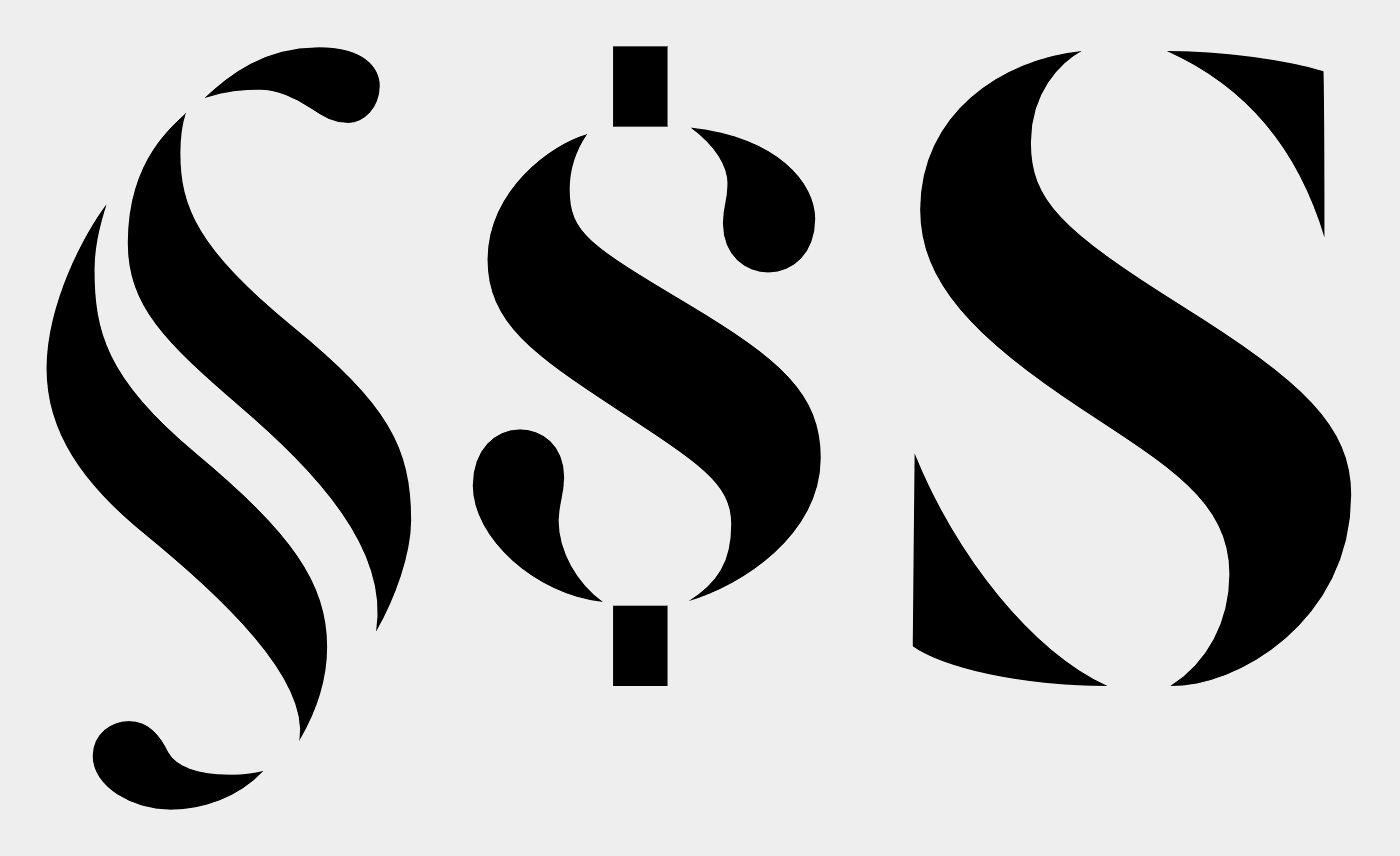
Suche Font(namen) aus meinem Logo.
Nun zu meinem Anliegen
Ich habe mein Logo erstellt mit einer Font dessen Name ich nicht mehr weiß.
Hier ein Bild
Ich habe mal so weit den Rest skizziert, wie ich meine die Font in Erinnerung zu haben:
Es handelt sich dabei Entweder um ein "S" oder um ein "§" doch ich bin mir sicher das es ein "§" war.
Leider habe ich auch keine weiteren Dateien mehr außer ein JPEG.
Ich hoffe mir kann hier geholfen werden die Font zu finden, bin aber voller Zuversicht.
ich nehme an, du brauchst eine vektor-version deines logos. wenn du die original-daten nicht mehr hast, baust du das ding in 5 minuten in einem vektor-programm deiner wahl nach. ist 30 mal schneller als den font zu suchen.
Ich hab das mal probiert, hat genau 2min 42sek gedauert:
Muss dazu alleredings beichten, dass Corel schon lief.
Schau Dir mal klassizistische Antiquas (Didot, Walbaum, Bodoni etc.) an, die Formensprache Deines Logos könnte auf eine solche Schriftart hindeuten.
Als Laie? Dafür habe ich auch echt leider keine Zeit. Suche eben die Font
Dafür sollte man sich schon etwas Zeit nehmen, um sich grundlegende Zeichenfunktionen anzueignen, mit denen sich beispielsweise solch ein Logo sehr schnell frei zeichnen lässt, ohgne das man dazu erst lange nach einem Font oder anderem vorgegebenen Rohmaterial suchen muss. Anleitungen für den Einstig in das Zeichnen mit einer Vektorgrafik gibt es beispielsweise auf YouTube zu Hauf.
Letztlich spart man sich durch ein wenig Wissen, wie man eine einfache Grafik selbst zeichnet wesentlich mehr Zeit, als man für diew Übung aufgewendet hat.
1) Geh auf www.Myfonts.de
2) Im Suchfeld »Didone« eingeben
3) Bei den dann angezeigten Schriften im Musterbuchstabenfeld »§S« eingeben
4) auf die Narziss von Hubert Jocham stoßen und anklicken
5) rechts »view all XXX fonts« anklicken
6) die dann angezeigte Liste durchsuchen und zum Beispiel auf diese hier stoßen:
Dauer der Suche: 2 Minuten  :-D
Und da gibt es noch eine Reihe weiterer Schriften, die Du sichten könntest, wenn Dir dieses Ergebnis nicht dicht genug dran ist.
Leider ist die Schriftart nicht dabei. Ich möchte noch mal darauf hinweisen das es die gesuchte Schriftart sein muss.
Mit dem nachzeichnen by e-learing ist kein Problem im Sinne der Fähigkeit.
Hier meine Nachzeichnung.
Stimmt mich zwar noch nicht zufrieden, aber ich bin zuversichtlich.
*Zusatz: Es handelt sich auch um eine Kostenlose Schriftart.
Ein Tipp fürs nächste Mal: Das wäre ein sehr hilfreicher Eingangshinweis für die Suche gewesen, weil er von vornherein zehntausende kostenpflichtige Schriften ausschließt, die man dann bei der Suche gar nicht hätte berücksichtigen müssen.
Leider ist die Schriftart nicht dabei. Ich möchte noch mal darauf hinweisen das es die gesuchte Schriftart sein muss.
Meine Darlegung des Suchweges diente auch mehr dazu, Dir zu zeigen, wie man bei der Suche vorgehen könnte. Um weiterzukommen, würde man nach dieser ersten Suche alle ähnlichen Schriften auswählen und bei jeder einzelnen noch einmal gesondert all jene Schriften unter die Lupe nehmen, die für die Ausgangsschrift als ähnlich empfohlen werden. Das kann eine zeitraubende Angelegenheit sein – und deswegen hat der geschätzte Kollege Catfonts nicht Unrecht, wenn er schreibt, dass der Aufwand, das Logo nachzubauen, geringer sein könnte als die Suche nach dem Originalfont.
Aber gut, Du sucht genau die Schrift, die Du damals zur Erstellung des Logos verwendet hast. Dann man andersherum gefragt: Besteht die Möglichkeit, dass Du diese Schrift noch hast (auf einer Schriften-Sampler-CD oder ähnlichem)? Beziehungsweise: Woher beziehst Du denn normalerweise Deine Schriften (Plattformen, Drittanbieter, Hersteller)? Vielleicht kommt man auf diesem Weg weiter.
Ein Tipp fürs nächste Mal: Das wäre ein sehr hilfreicher Eingangshinweis für die Suche gewesen, weil er von vornherein zehntausende kostenpflichtige Schriften ausschließt, die man dann bei der Suche gar nicht hätte berücksichtigen müssen.
Meine Darlegung des Suchweges diente auch mehr dazu, Dir zu zeigen, wie man bei der Suche vorgehen könnte. Um weiterzukommen, würde man nach dieser ersten Suche alle ähnlichen Schriften auswählen und bei jeder einzelnen noch einmal gesondert all jene Schriften unter die Lupe nehmen, die für die Ausgangsschrift als ähnlich empfohlen werden. Das kann eine zeitraubende Angelegenheit sein – und deswegen hat der geschätzte Kollege Catfonts nicht Unrecht, wenn er schreibt, dass der Aufwand, das Logo nachzubauen, geringer sein könnte als die Suche nach dem Originalfont.